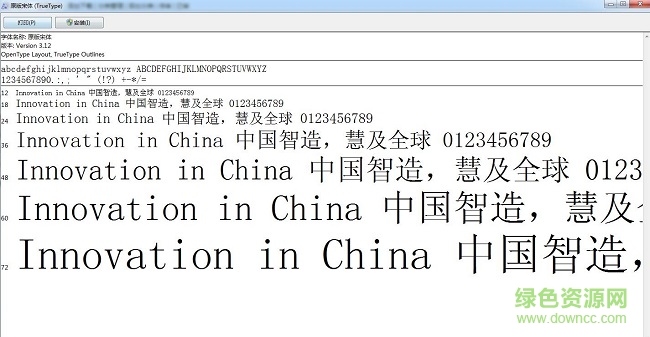
原版宋體
simsun.ttc原版宋體是一款橫細(xì)豎粗的經(jīng)典宋體字體,細(xì)節(jié)豐富,結(jié)構(gòu)嚴(yán)謹(jǐn)規(guī)范,線條粗細(xì)適當(dāng),多用于印刷設(shè)計(jì)等方面,給人的視覺(jué)感受非常舒服,需要的朋友快來(lái)下載吧!
宋體特點(diǎn)
宋體結(jié)構(gòu)方正勻稱(chēng),橫細(xì)直粗,便于刻版,閱讀醒目,是16世紀(jì)以來(lái)漢字的主要印刷體。當(dāng)前出版物上的常用字體,除宋體外(如:小),還有仿宋體(小)、楷體(小)、黑體(小)等。